米芾《论草书帖》,又称《草圣帖》、《论书帖》、《张颠帖》,纸本,草书,纵24.7厘米、横37厘米,台北故宫博物院藏,约书于北宋哲宗元祐二年(1087)。
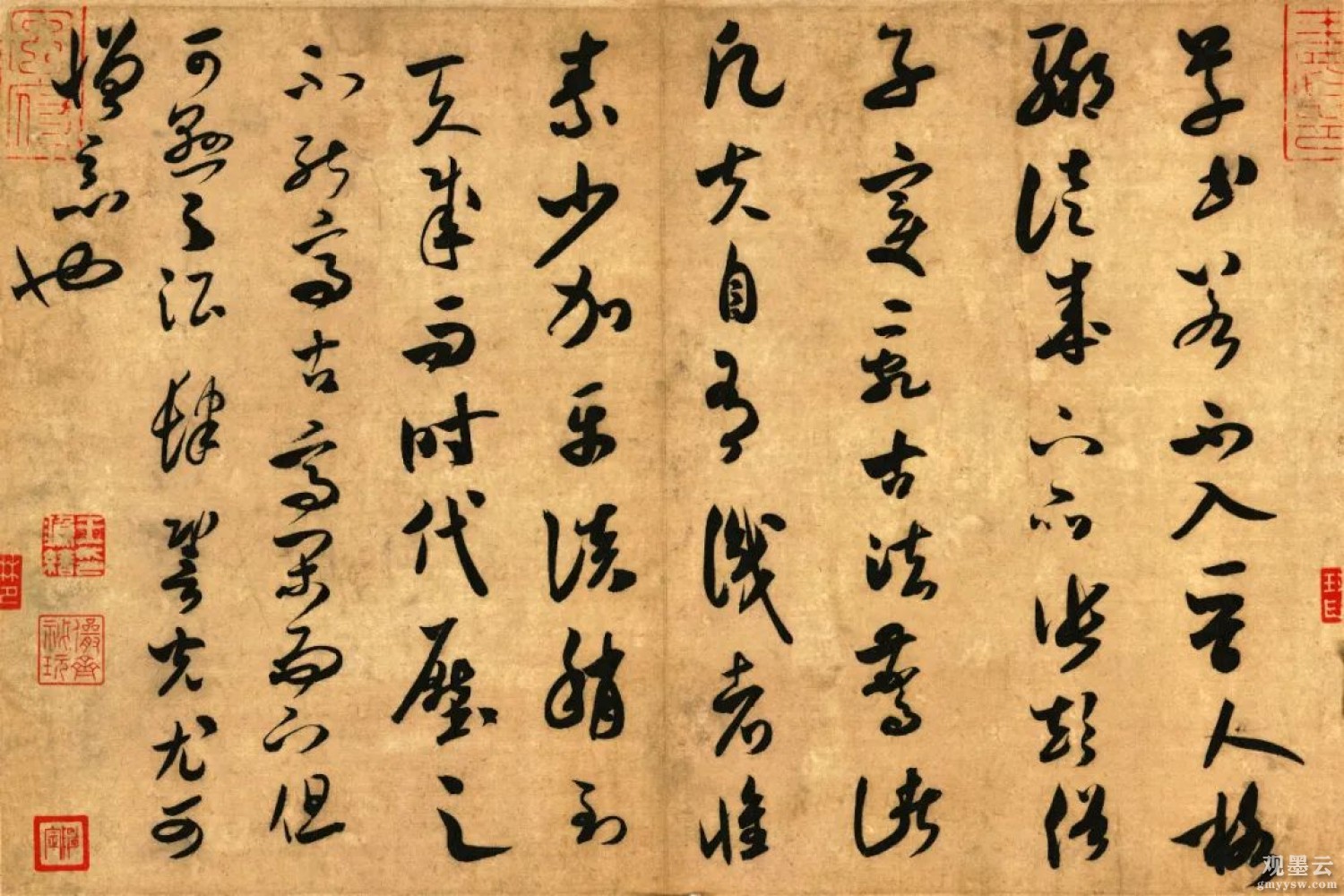
【释文】草书若不入晋人格,辄徒成下品。张颠俗子,变乱古法,惊诸凡夫,自有识者。怀素少加平淡,稍到天成,而时代压之,不能高古。高闲而下,但可悬之酒肆。辩光尤可憎恶也。
【译文】草书如果没有晋人的风骨,则仅仅成了下品。而唐代的书家张颠,改变了自古以来的书法风格,看孙大娘舞剑创造的草书,惊世骇俗,自有人赏识。怀素学天上的行云,草书平淡中浑然天成。如今时代变了,写的草书虽不能超越古人,但是成为闲情逸致,挂在酒馆里,作为酒后的一种的消遣,还是无可非议的。辩光尤其厌恶。
::徒(tú ) 白白地;只;仅仅。::高古(gāo gǔ ) 高雅古朴。::酒肆(jiǔ sì ) 卖酒或供人饮酒的地方。::辩光(biàn guāng ) 唐朝后期书法家,字登封,俗姓吴,永嘉(浙江温州)人。::憎恶(zēng è ) 憎恨,厌恶。